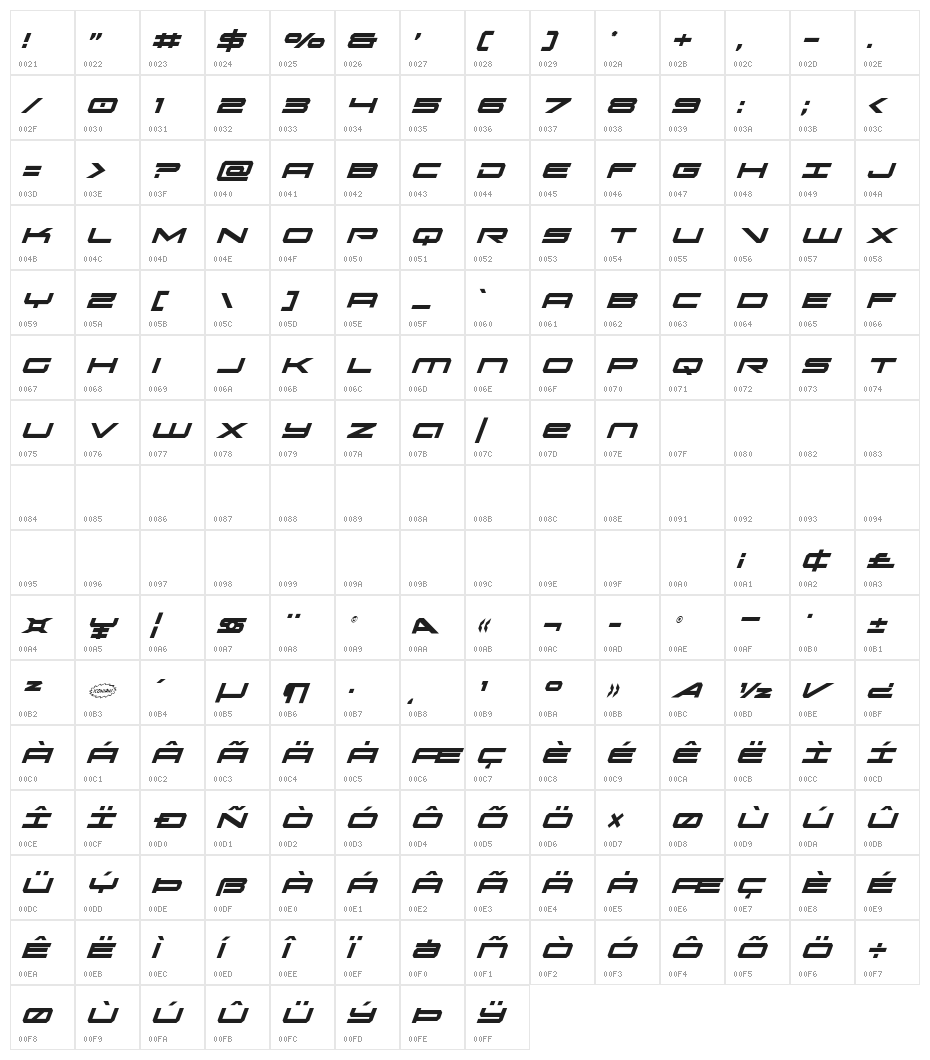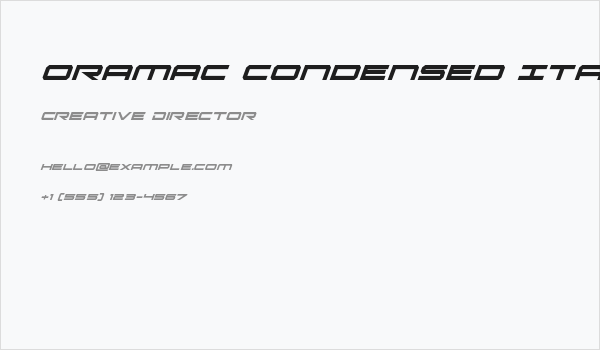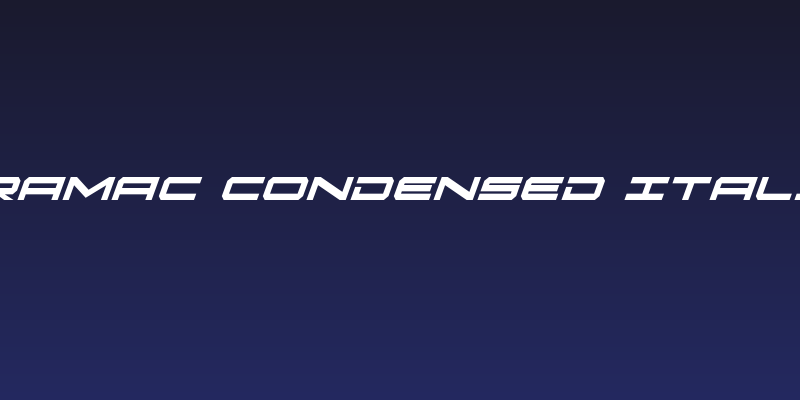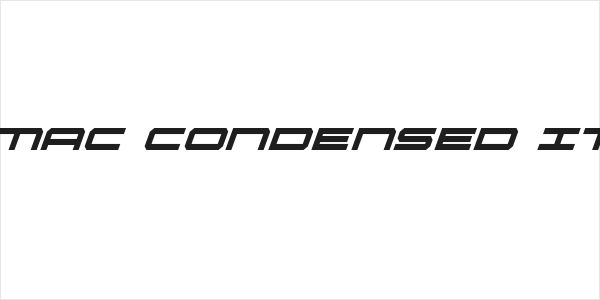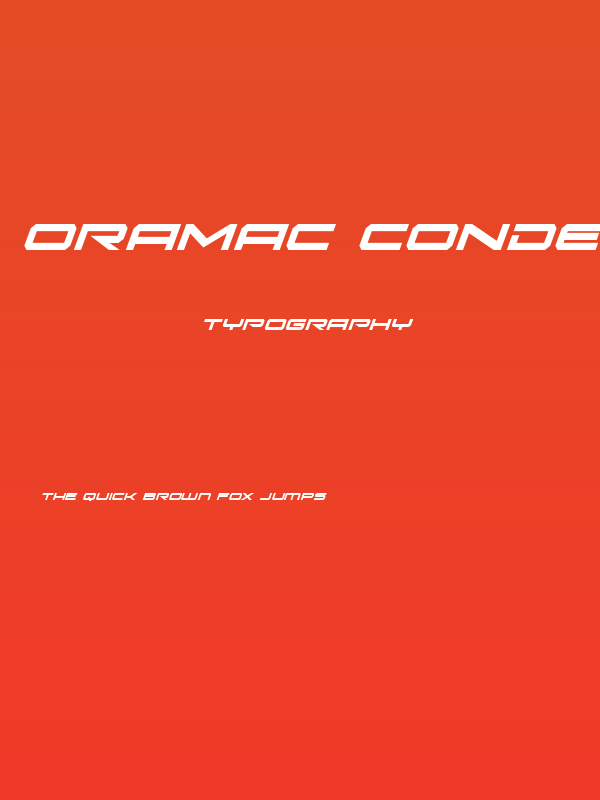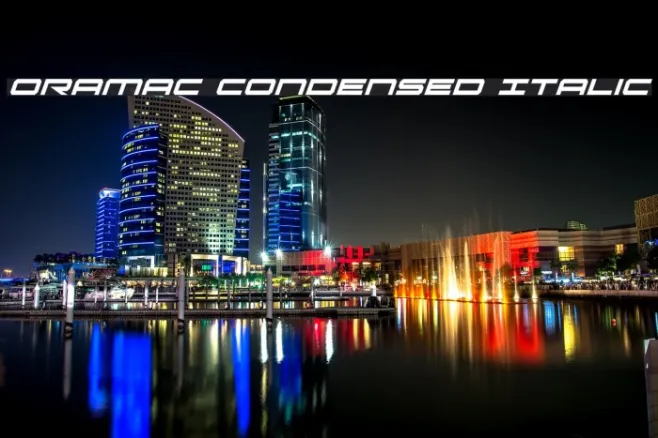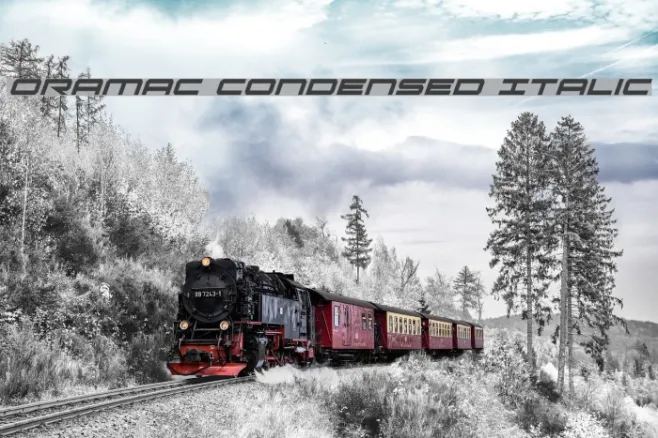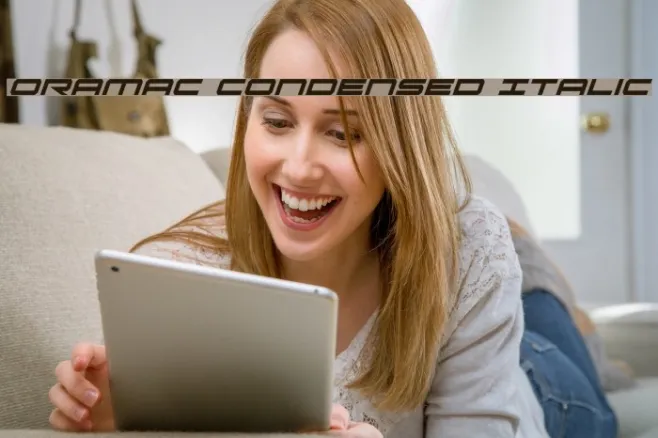
Oramac Condensed Italic Font
✎ Futuristic
| Kategorien | Futuristic |
| Anwendungsfall | Logos, Headlines, Posters |
| Vorgeschlagene Projekte | Ideal for technology branding, sports team logos, automotive advertisements, and sci-fi themed designs. |